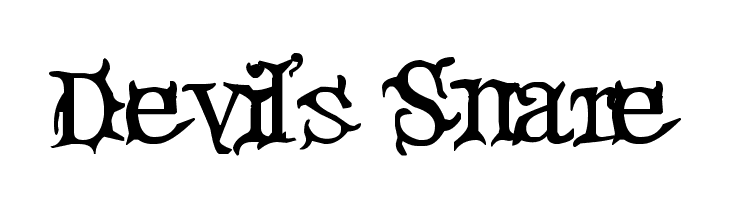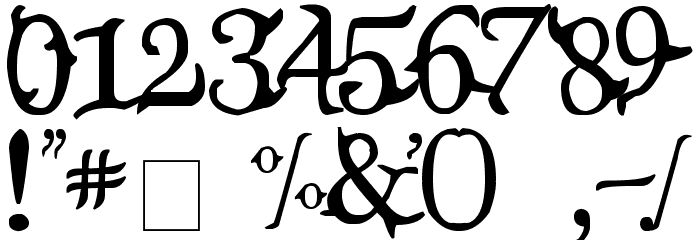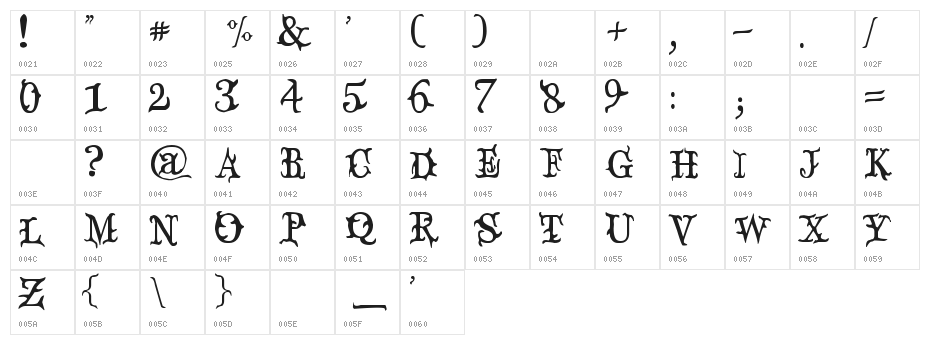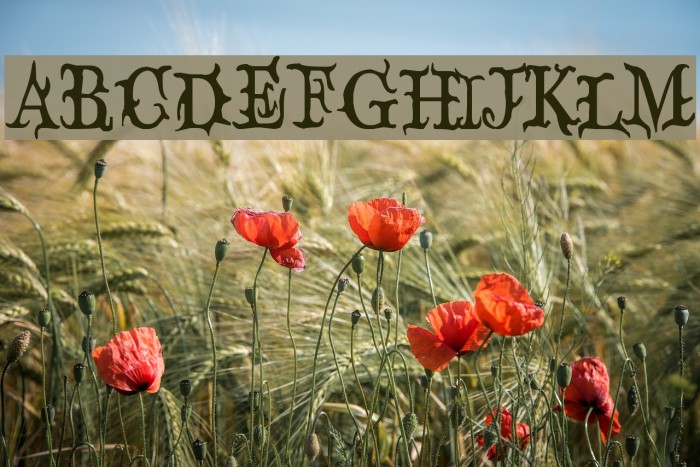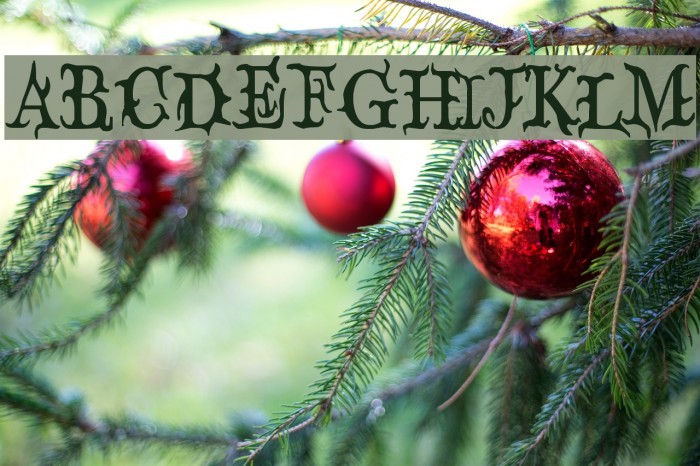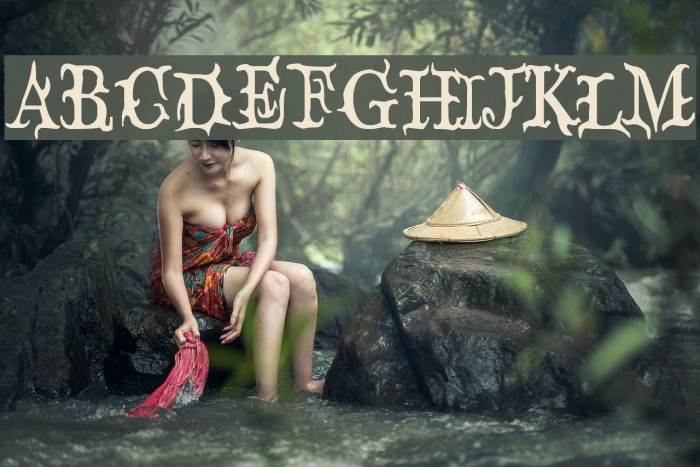
Devil's Snare Font
| Категория | Gothic |
| Общий стиль | Gothic, Fantasy |
| Рекомендуемые проекты | Ideal for fantasy-themed projects, book covers, movie posters, or any design requiring a dramatic and mystical touch. |